20 tipografías gratuitas made in España y Latinoamérica
Son diferentes entre sí, pero tienen algo en común: son gratuitas y han sido diseñadas por latinoamericanos y españoles.
La tipografía, ese elemento esencial en todo tipo de proyecto que puede convertir un trabajo en una obra magistral o, por el contrario, deslucir el esfuerzo y horas de trabajo detrás de un gran proyecto con su mala elección. Saber elegirlas y combinarlas es esencial, pero para poder hacerlo con maestría es indispensable contar con un buen arsenal de opciones entre las que elegir. Anteriormente ya habíamos seleccionado 20 fuentes gratuitas de tipógrafos iberoamericanos, pero somos de la creencia de que muchas tipografías nunca son suficientes, así que hemos seleccionado otras 20 fuentes tipográficas que cuentan con la letra 'ñ' entre sus glifos, pues han sido creadas por diseñadores latinoamericanos o españoles.
Salome, de Atipo (@atipo)
Una tipografía didona con grandes exagerados contrastes entre sus rasgos más gruesos y aquellos más finos, diseñada por RaúlGarcía del Pomar e Ismael González, fundadores del estudio español Atipo, que se puede descargar de manera gratuita en su versión normal o con el método "pay what you want" la familia completa.
Sansita, de Pablo Cosgaya & Omnibus-Type
Diseñada en cuatro pesos, esta tipografía explora la elegancia de una tipografía inspirada en la caligrafía manual, que bebe también del lettering y funciona perfectamente en proyectos de branding y packaging gracias a la personalidad que confiere a los textos.
Jockey, de José Scaglione & Veronika Burian
Como su propio nombre hace imaginar, esta tipografía ha sido diseñada por inspiración de los carteles de las carreras de caballos creados por un diseñador argentino anónimo durante la década de los años 30.
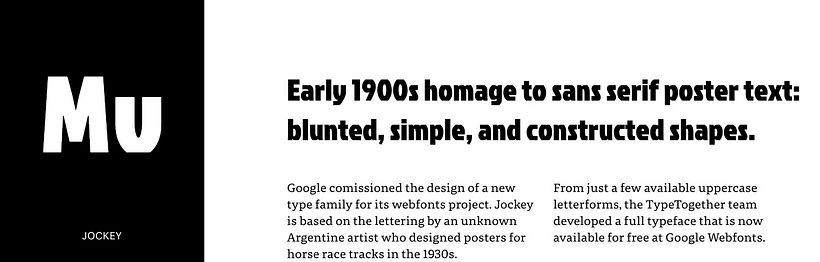
Granaína, de Sergio Arredondo (Zer)
Haciendo gala del marcado carácter y desparpajo de la ciudad de Granada, esta tipografía nace a imagen y semejanza de los letreros de cerámica que pueden encontrarse en las calles de la ciudad que alberga La Alhambra, el monumento más visitado de España.
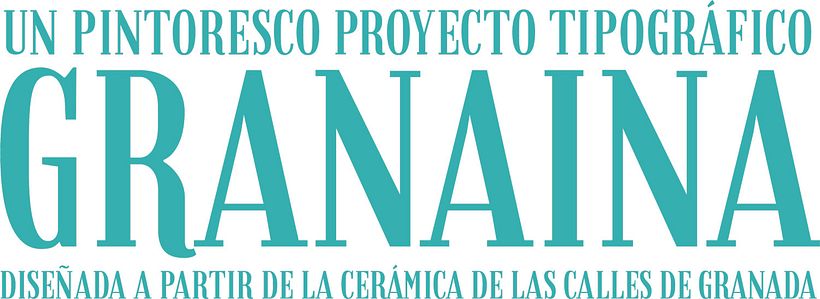
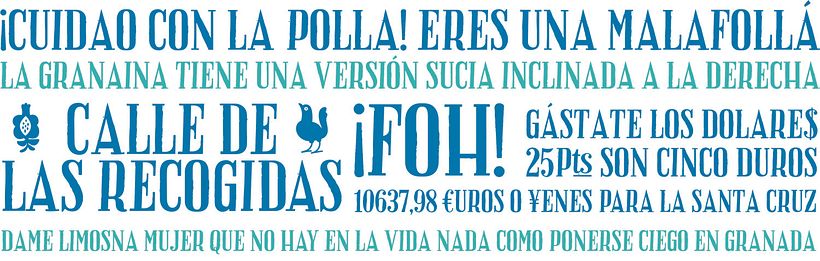
Uriarte 2017, de Luis G. Córdova M. (GüichoGokú)
También basada en una de las placas de cerámica decorada de la ciudad fue diseñada esta tipografía, aunque esta tiene un origen geográficamente a la anterior, concretamente en la ciudad mexicana de Puebla.
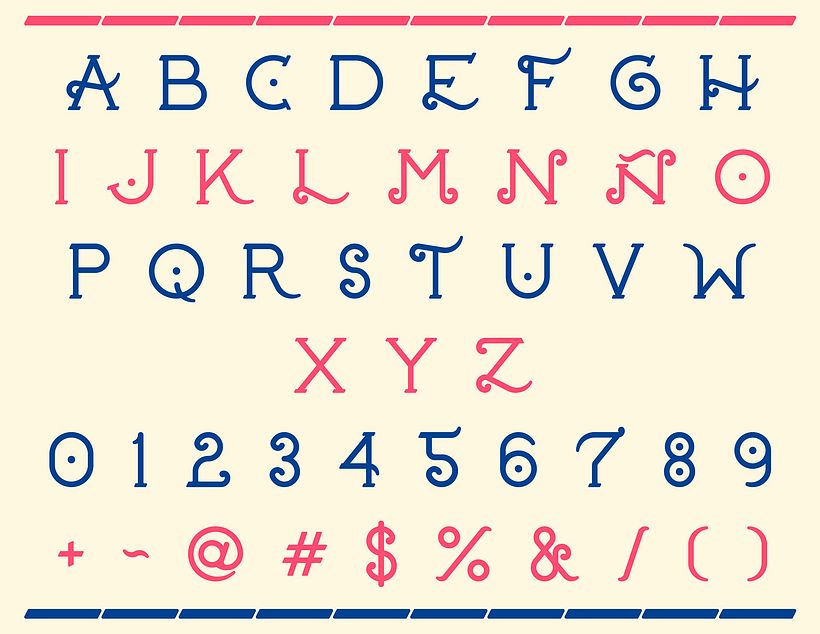
Garnata, de Nano Torres y Juanjo Rivas (@juanjo_rivas)
De aspecto algo más moderno, pero inspirada en la misma ciudad del sur de España que Granaína es Garnata, una tipografía sin serifa diseñada a partir de la observación de los rótulos comerciales de la ciudad de Granada.
Black Pack, de Juanjo López (@juanjez)
Diseñada para llenar todo el espacio y convertir el espacio en una mancha negra "como el sobaco de un grillo", esta tipografía se puede descargar en cuatro estilos diferentes, cada uno con ocho anchos y un peso, que mezcla anchuras aleatoriamente. No es exactamente gratuita, pero sí está disponible en formato "pay what you want" para que tú mismo elijas cuánto quieres pagar por ella.
Circo, de Tano Veron
La tipografía creada por este diseñador argentino habla de la infancia, del color y de la diversión; de las tardes en el circo y de los atracones de dulces y chocolate. Y eso, por lo tanto, la convierte en una tipografía alegre y original.
Facunda, de Bu! Estudio Gráfico
Una tipografía condensada, diseñada por el estudio sevillano Bu!, en cinco estilos diferentes, incluido uno que aporta una sombra con profundidad a cada letra que promete cargar de personalidad cualquier proyecto en la que sea protagonista.
Fina, de Yai Salinas
Sus líneas son prácticamente imperceptibles, de ahí su nombre; pero su personalidad y las pequeñas serifas puntiagudas que la caracterizan la convierten en una tipografía hecha para destacar y marcar elegancia.
Cuatacho Typeface, de Jorge Alberto Martínez
Una de las historietas mexicanas más conocidas de todos los tiempos es la culpable de la creación de esta tipografía. La fuente, irregular y diseñada en un solo peso, está inspirada en la tipografía utilizada en los comics de Memín Pinguín.
Lletraferida, de Tipo Pèpel
Se trata de una tipografía didona, de mancha pesada, diseñada para ser utilizada en titulares o proyectos que precisen fuentes a gran tamaño. Además de los glifos habituales, Lletraferida incluye un juego de caracteres decorativos iniciales y finales, ligaduras y numerales superiores e inferiores.
Johanna, de Adrià Gómez
De aspecto moderno y en dos pesos diferentes, esta tipografía ha sido diseñada a partir de seis piezas modulares básicas que se combinan y componen los 147 glifos.
Lousiane, de Juanjo Rivas del Río
De estilo art nouveau, decorada con todo tipo de ligaduras y terminaciones, esta tipografía creada para la revista Neo2 es perfecta para imprimir carácter y llamar la atención sobre el propio texto en cualquier tipo de proyecto.
L'Engineer, de Ferdie Balderas
Fresca y sencilla, así es esta tipografía de carácter manuscrito que, sin embargo, se aleja mucho de la irregularidad de los caracteres tradicionales escritos a mano y abraza la sencillez de la tipografía informal y la escritura en mayúsculas.